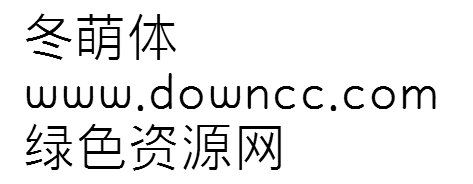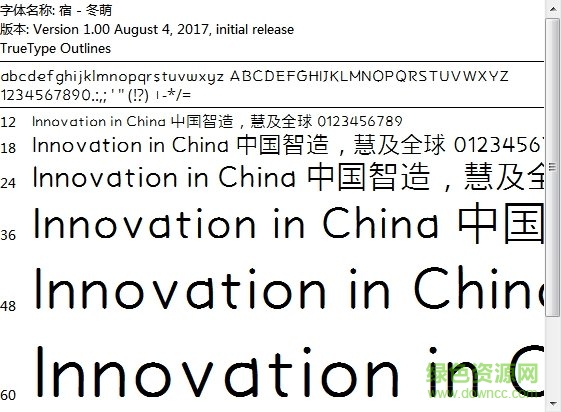
冬萌體字體
冬萌體是一款造型清爽、字跡清晰簡(jiǎn)約的系統(tǒng),給人悅目舒適的視覺(jué)體驗(yàn),讓你的內(nèi)容閱讀更加柔和,綠色資源網(wǎng)獨(dú)家推薦!
冬萌字體特色
冬萌體有著極其工整和端方的造型結(jié)構(gòu),類(lèi)似于常見(jiàn)的網(wǎng)頁(yè)字體,給人十分清晰大方的視覺(jué)辨認(rèn)感,整體效果十分出色。
宿冬萌體